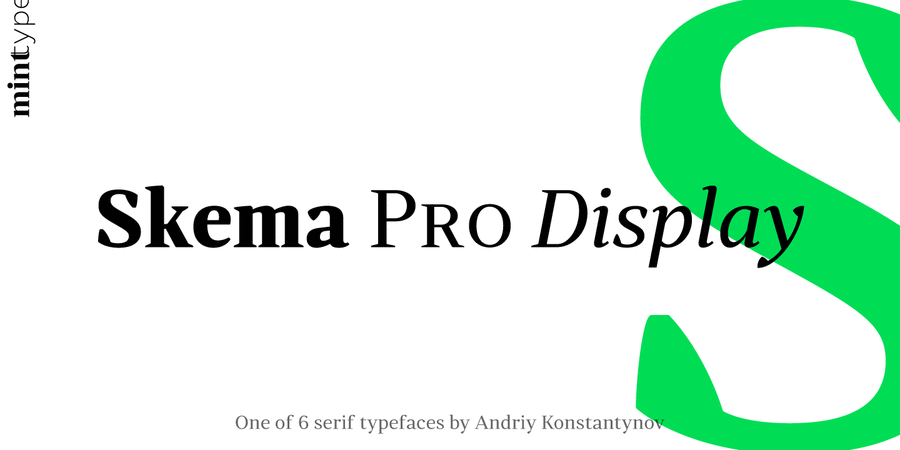
Skema Pro Display – контрастна гарнітура з великою висотою рядкових та вертикальною віссю контрасту. Типова заголовна гарнітура із тонкими зарубками та великими краплями.
Skema Pro – система з 6 антикв, кожна з яких має свій характер і призначення. Разом вони формують величезну супергарнітуру з 84 накреслень для будь-яких можливих завдань.
Сімейство Skema Pro розробив і випустив Андрій Константинов у студії Mint Type у 2017 році.
Асоціації з сімейством шрифтів Skema Pro DisplayОсобистість і характер гарнітури:
гармонійний, тонкий, легкий, технічний, сучасний, культурний, освічений, міський, точний, твердий, благородний, якісний, сріблястий, статичний, різкий, пафосний, гордий, дорогий, розкішний, модний, багатий, худий, витончений, делікатний, прохолодний, свіжий, добірний, елітний, красивий, ювелірний, майстерний, естетичний, знаменитий, дорогоцінний, оригінальний, дзвінкий, гострий, ввічливий, елегантний, пластичний, динамічний, жіночний, стійкий, формальний, переконливий, авторитетний, мотивуючий, щільний, ефектний, театральний, драматичний, пристрасний, тісний, сильний, помітний, яскравий